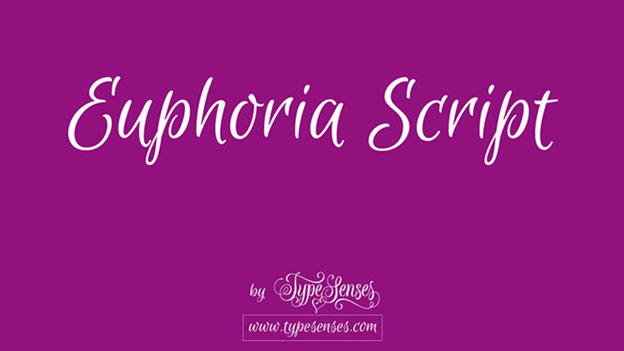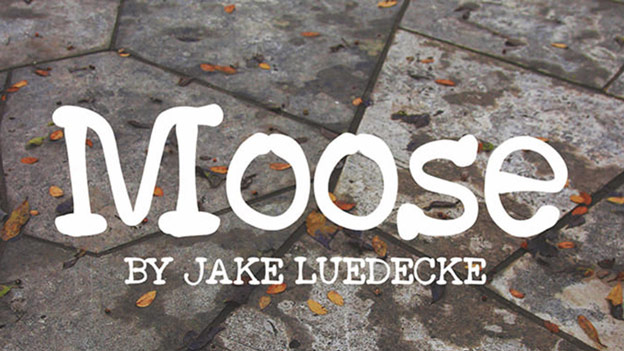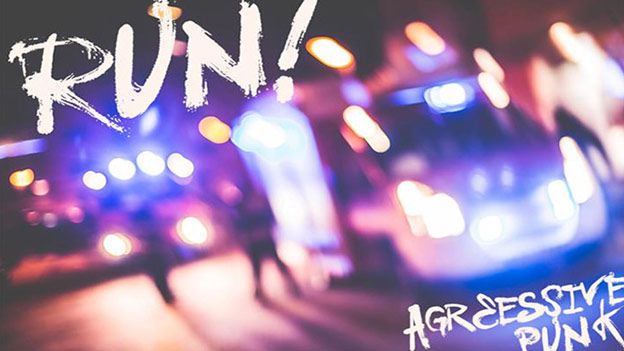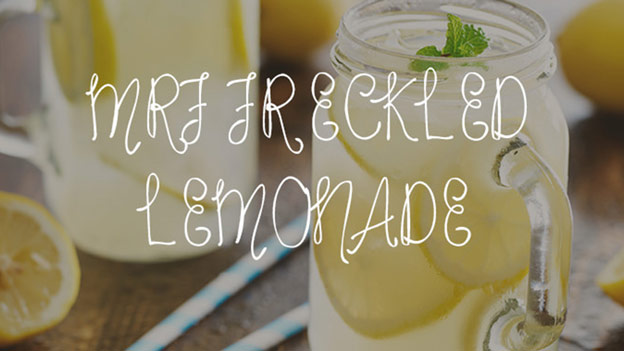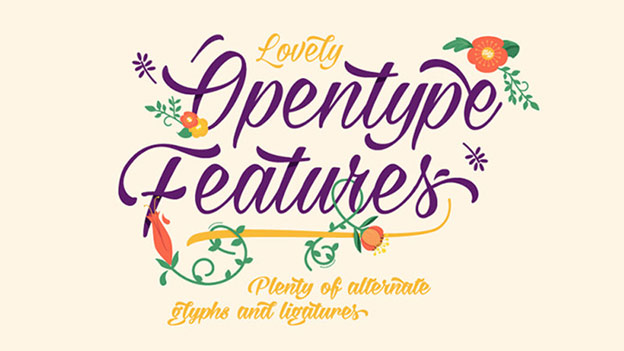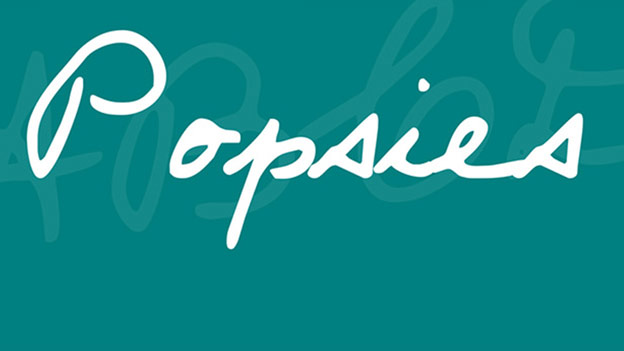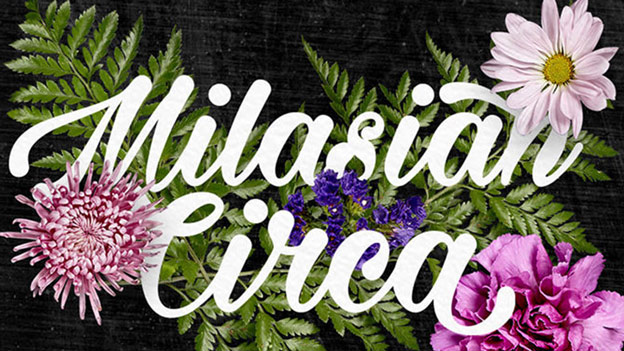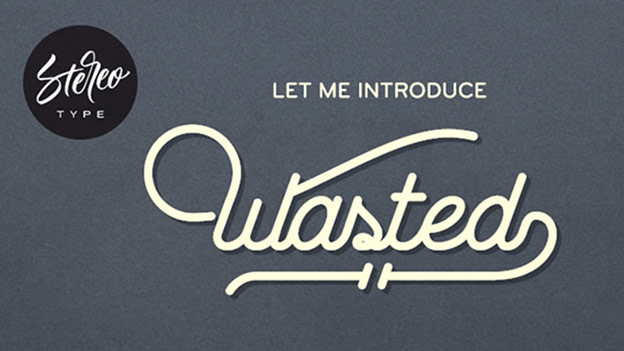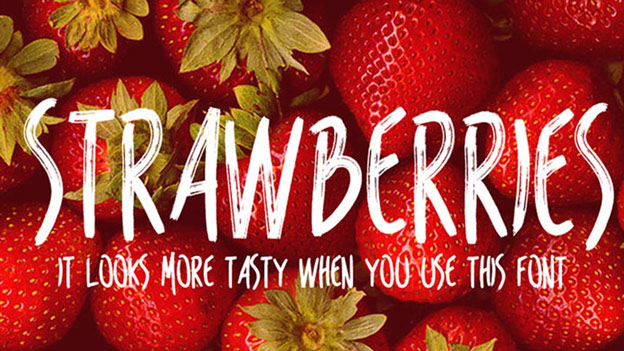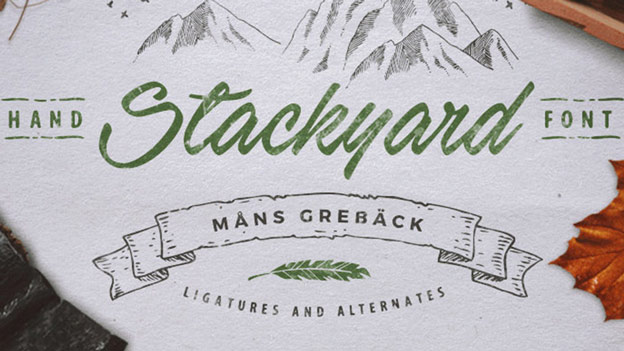
Tổng hợp 1000+ font chữ viết tay cực đẹp miễn phí
Font chữ viết tay thường được dùng trong thiết kế đồ họa như thiết kế thiệp mời, banner, thiết kế ảnh, hay các thầy cô giáo có thể dùng font chữ viết tay để thiết kế bìa giáo án. Vì vậy font chữ viết tay được sử dụng ở rất nhiều nội dung khác nhau, với nét chữ phóng khoáng, đậm phong cách nghệ thuật typography. Dưới đây là tổng hợp danh sách các font chữ viết tay để bạn tải xuống và sử dụng.
1. Tải 8 font chữ viết tay mới nhất 2022
2. Tổng hợp 1000+ font chữ viết tay
Zuey Handwriting font
Noelan Script font
Hallelujah font
Handycheera font
Mightype font
Nothern Lights font
Wildera font
Selima
Yunus Font
Reis Font
Bellaboo Font
Fofer Font
California Sans Font
Ruffle Beauty Font
The Skinny Font
Gunny Rewritten
Halo Handletter
Yore Font
Whatever It Takes
Before Breakfast Font
Engine Font
Chomp Font
Haiku’s Script
Pops Font
GoodDog Font
J.D Handcrafted
Journal Font
Daniel Font
Mawns’ Handwriting
Bispo Nova
Billy Font
Novito Nova Font
Bakery
She Always Walks Alone
Variane Script Font
Shorelines Script
Reis
Stackyard
A HandMade Font
Cheddar Jack
Kitsune Udon
BeWicked
Euphoria
Moose font
Vtks Love U
MRF Freckled Lemonade
Milasian
Wasted
Scriptina Font Family
Popsies Font
Milasian Circa
Ruffle Beauty